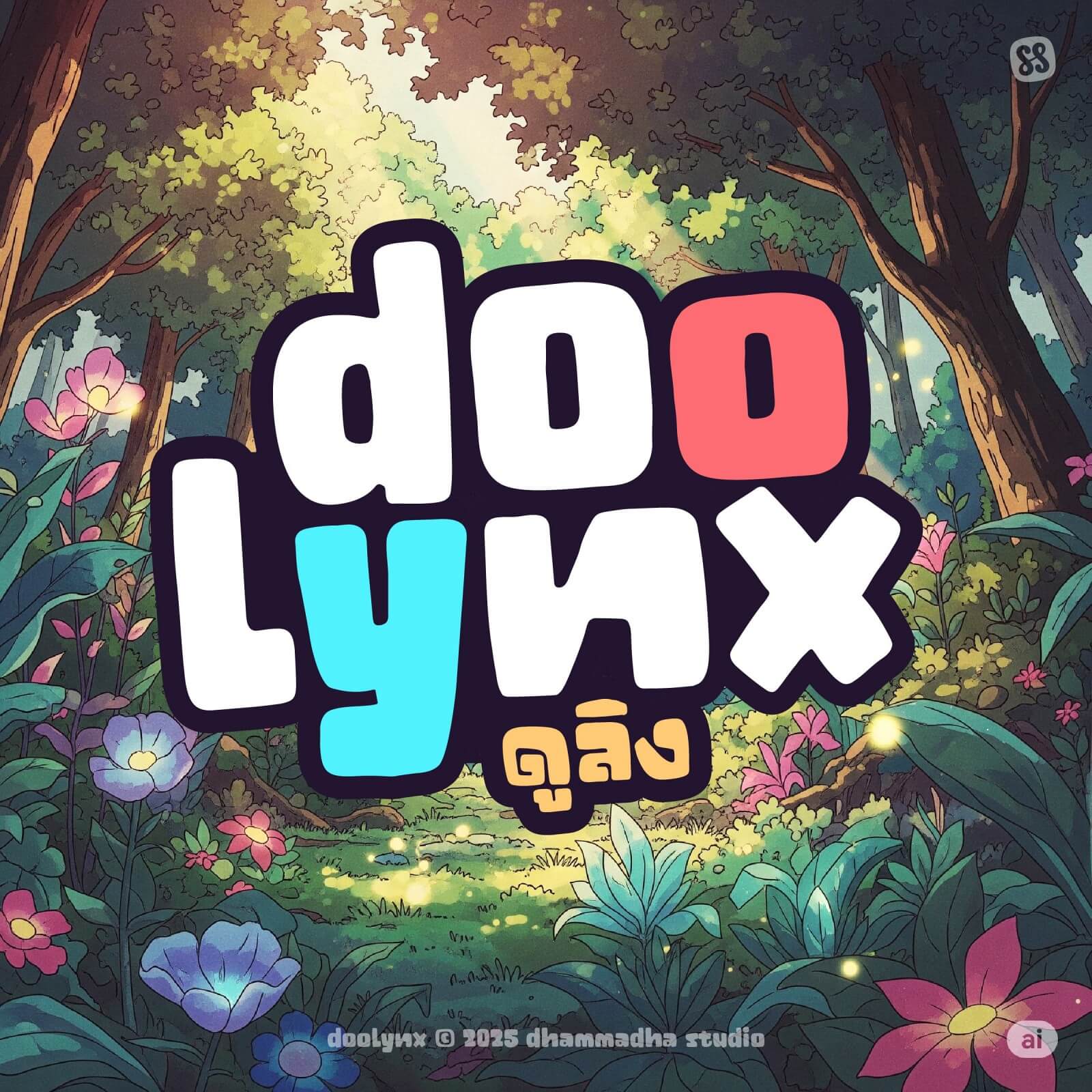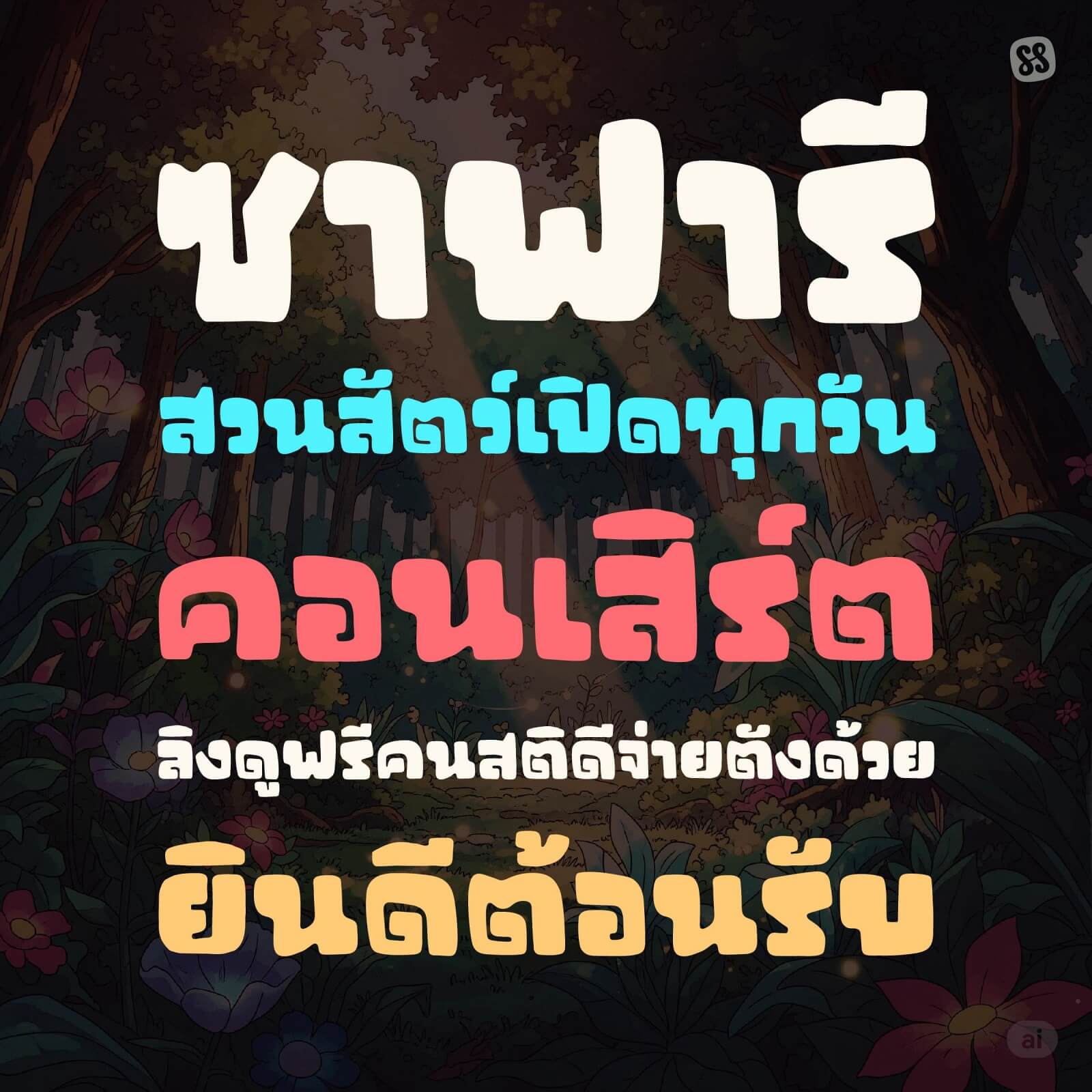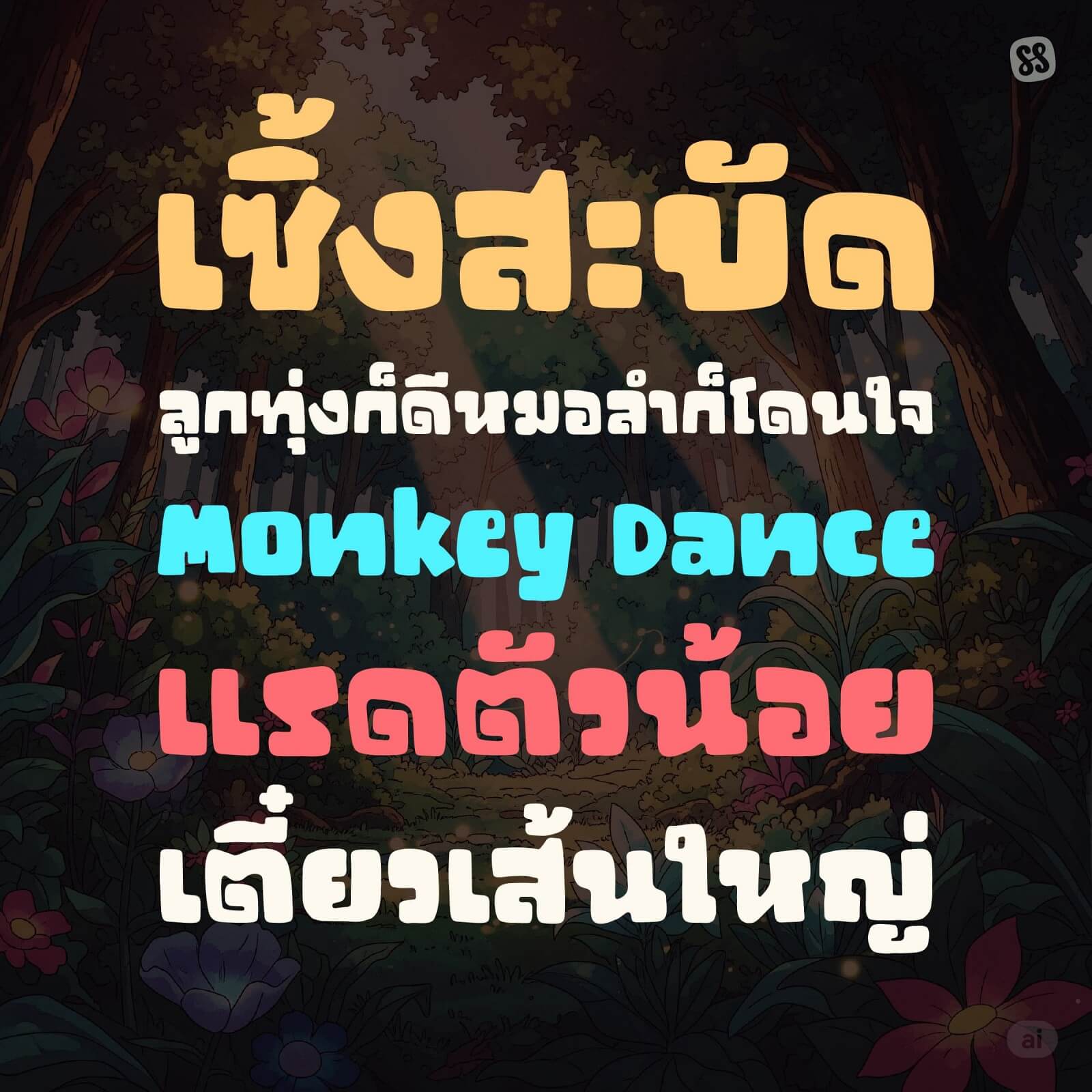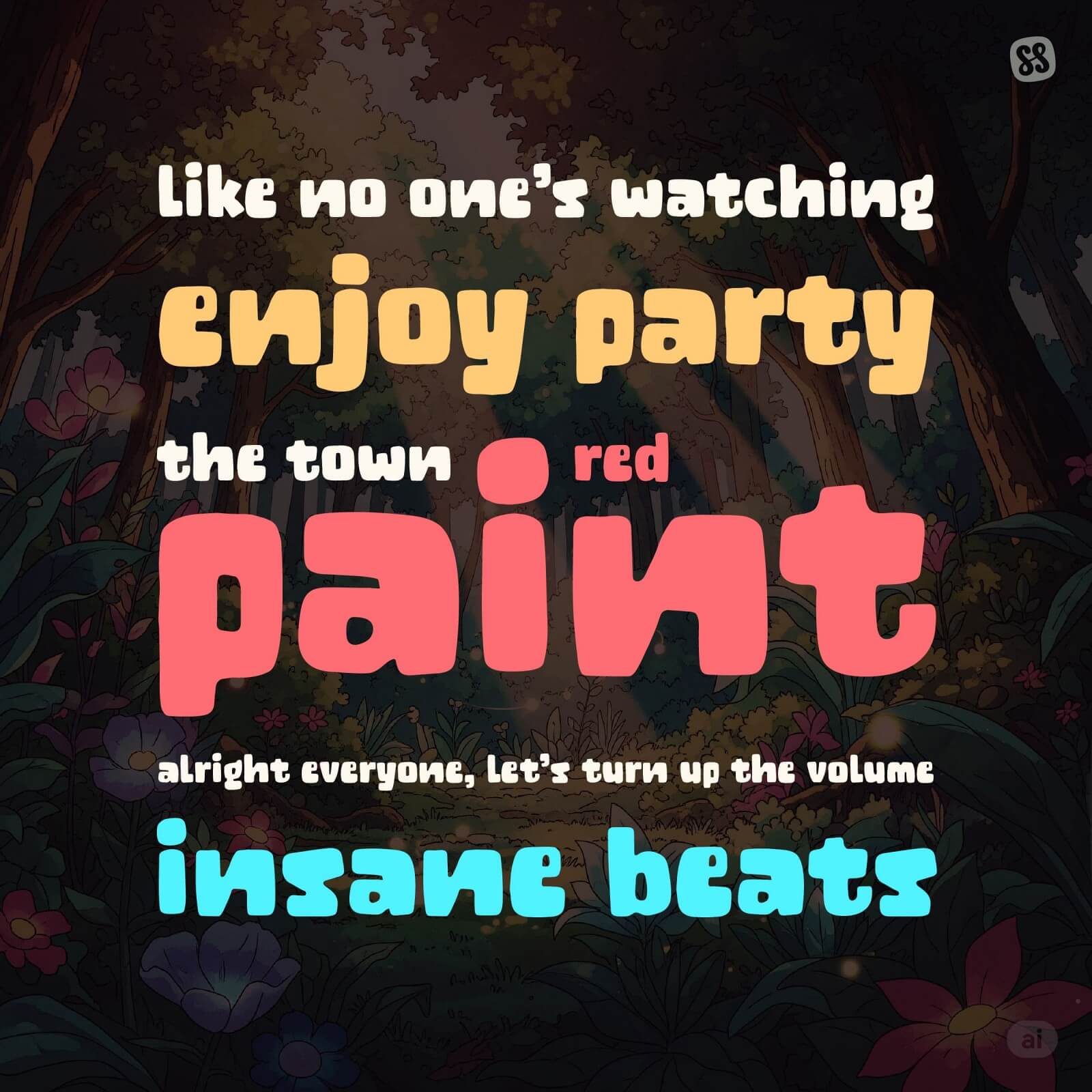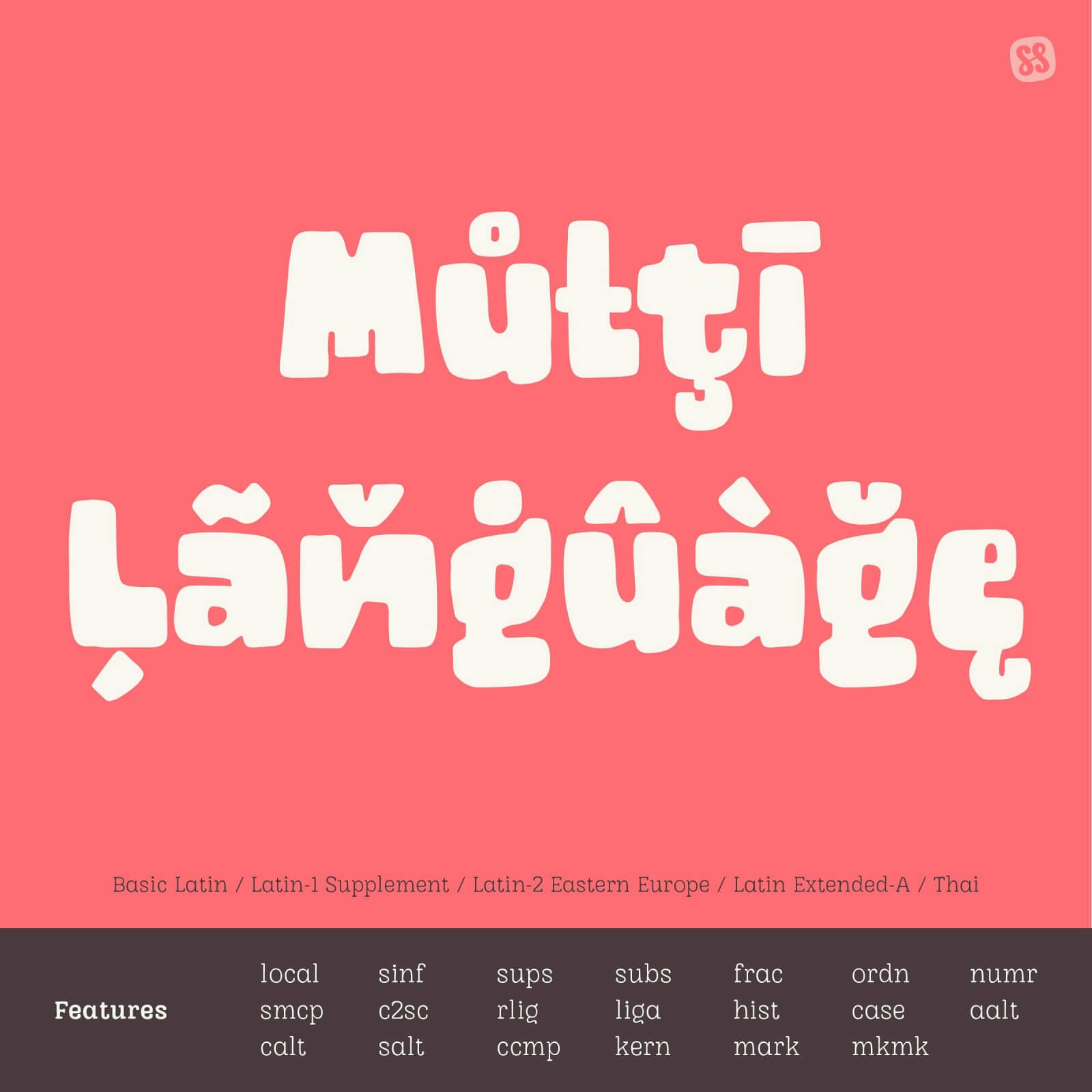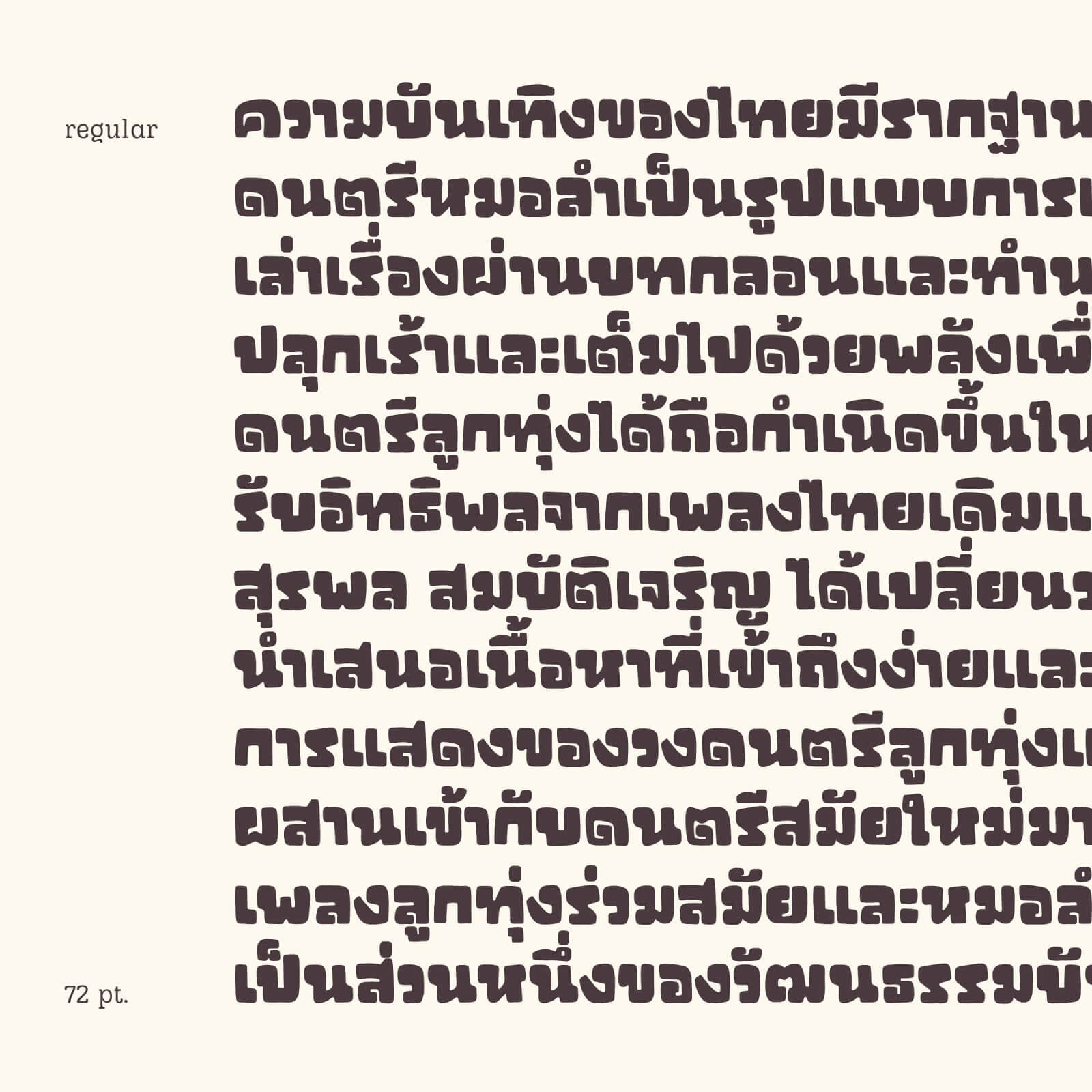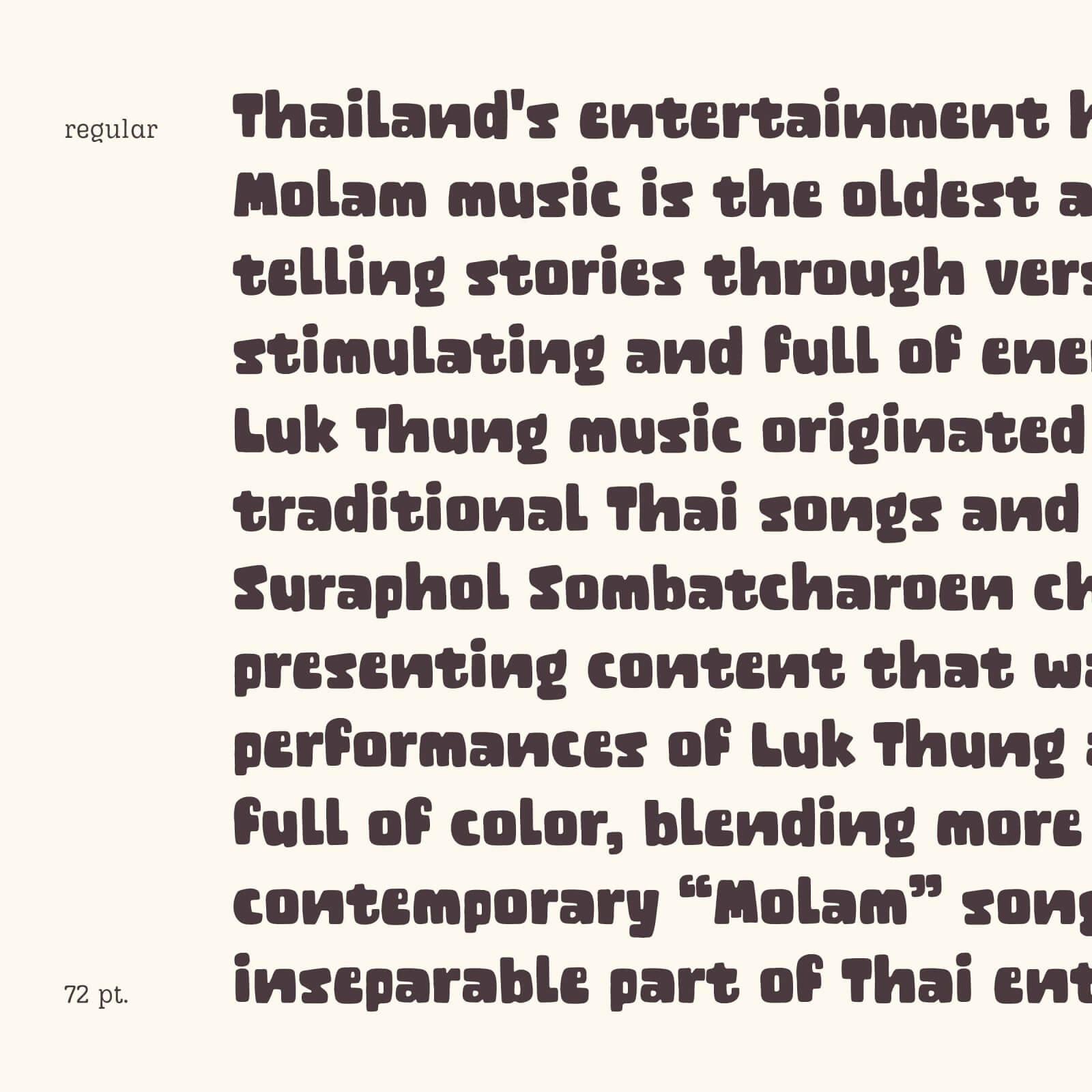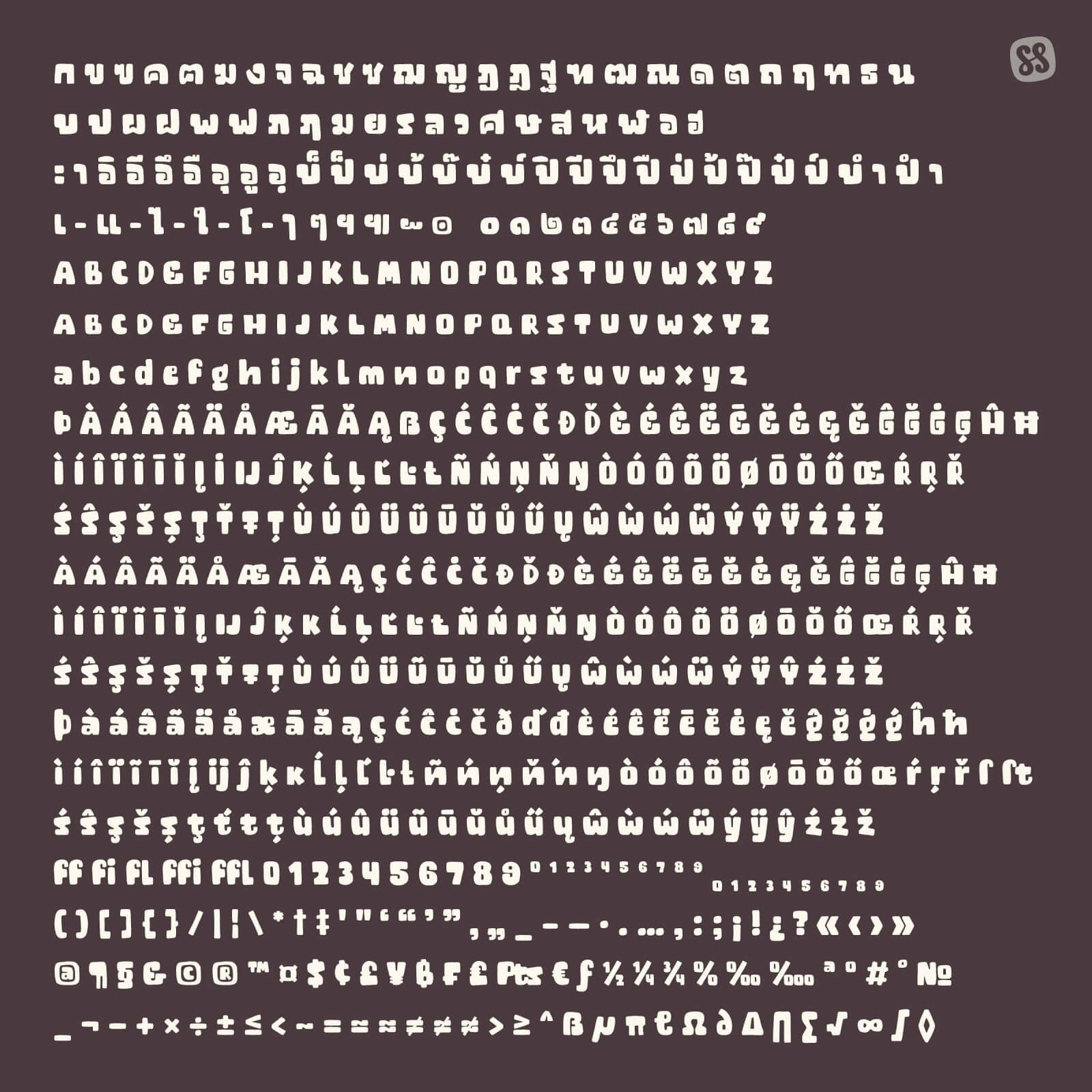
เปลี่ยนงานให้ดูมีชีวิตชีวาขึ้นอีกขั้น!! ด้วย “ดูลิง | DOOLYNX” ฟอนต์ดิสเพลย์วาดมือสุดคิวท์ ที่จะนำความคิดสร้างสรรค์อันไร้ขีดจำกัดมาสู่โปรเจกต์ของคุณ กับรูปทรงที่โค้งมน อวบอ้วน ให้ความรู้สึกสนุกสนานโดดเด่นไม่เหมือนใคร
เหมาะสำหรับทุกความต้องการในงานสร้างสรรค์ของคุณ ด้วยสไตล์การวาดเส้นที่ดูเป็นธรรมชาติและขี้เล่น ทำให้ “ดูลิง” เป็นตัวแทนของความน่าสนใจและมีส่วนร่วมในธีมที่หลากหลาย
เติมเต็มไอเดียของคุณด้วยความมีชีวิตชีวาและสัมผัสที่เป็นธรรมชาติ ด้วยลูกเล่นที่สนุกสนานของ “ดูลิง | DOOLYNX” ไม่ว่าคุณจะทำงานในธีมที่สนุกสนานหรืองานออกแบบที่สดใส ฟอนต์นี้คือตัวเลือกที่เหมาะสมที่สุดที่จะทำให้โปรเจกต์ของคุณโดดเด่น
ให้ “ดูลิง” เพิ่มความอบอุ่นและเสน่ห์ที่โดนใจให้กับผลงานสร้างสรรค์ของคุณ
ชุดฟอนต์ “ดูลิง” ประกอบด้วยฟอนต์ 1 น้ำหนัก 1 ฟอนต์
• DOOLYNX Regular